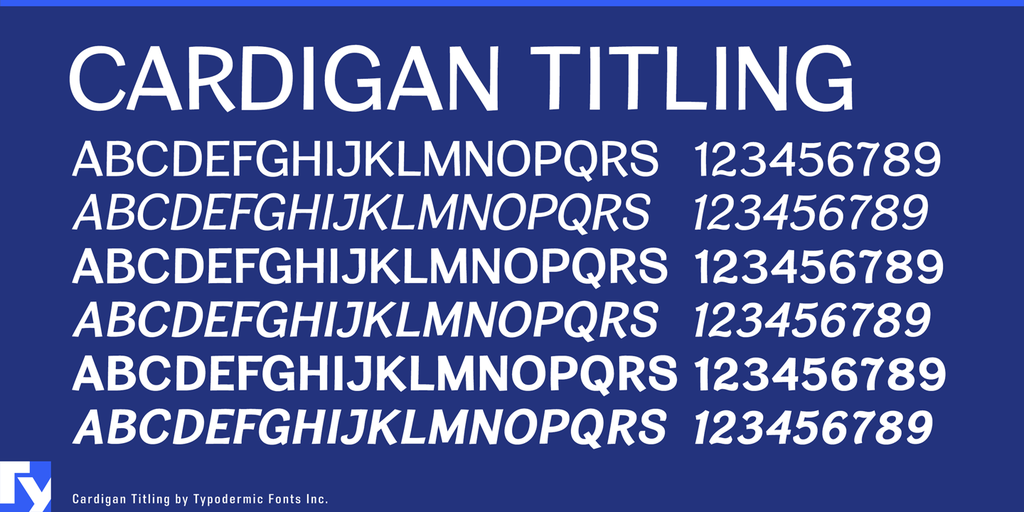
A Cardigan é uma tipo de fonte sans-serif casual perfeita para ambientes naturais e envolventes. Embora seu estilo seja descontraído, as formas das letras são claras e convencionais, tornando-a um dos raras fuentes deste tipo que se comportam bem em grandes quantidades de texto. As itálicas têm uma aparência naturalmente mais suave do que os uprights, mas mantêm-se práticas; não são ostentosas. A Cardigan está disponível nas três pesos básicos, incluindo as itálicas. Para uma versão da Cardigan com minúsculas, consulte o famoso família de tipo regular da Cardigan. Ainda que a Fonte Cardigan seja um elemento casual, sua natureza despojada e natural pode ser incorporada em qualquer estilo de design gráfico, tornando-a uma escolha ideal para um vasto leque de projetos. Seja você designer de blogs, criador de conteúdo ou até mesmo ilustrador, a Cardigan não apenas se destaca por sua aparência, mas também pela sua versatilidade e facilidade em manuseio. Numa era cada vez mais digitalizada, uma fonte que oferece essa combinação de casualidade e naturalidade é particularmente valiosa.